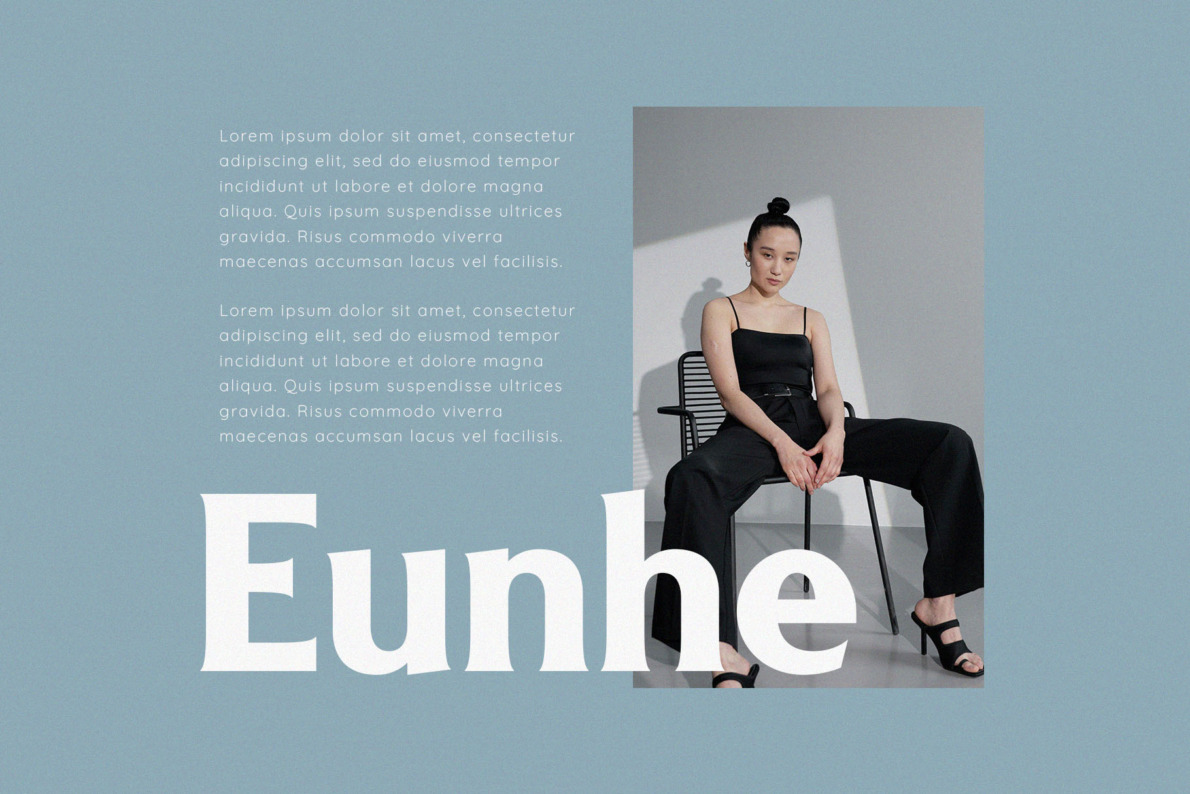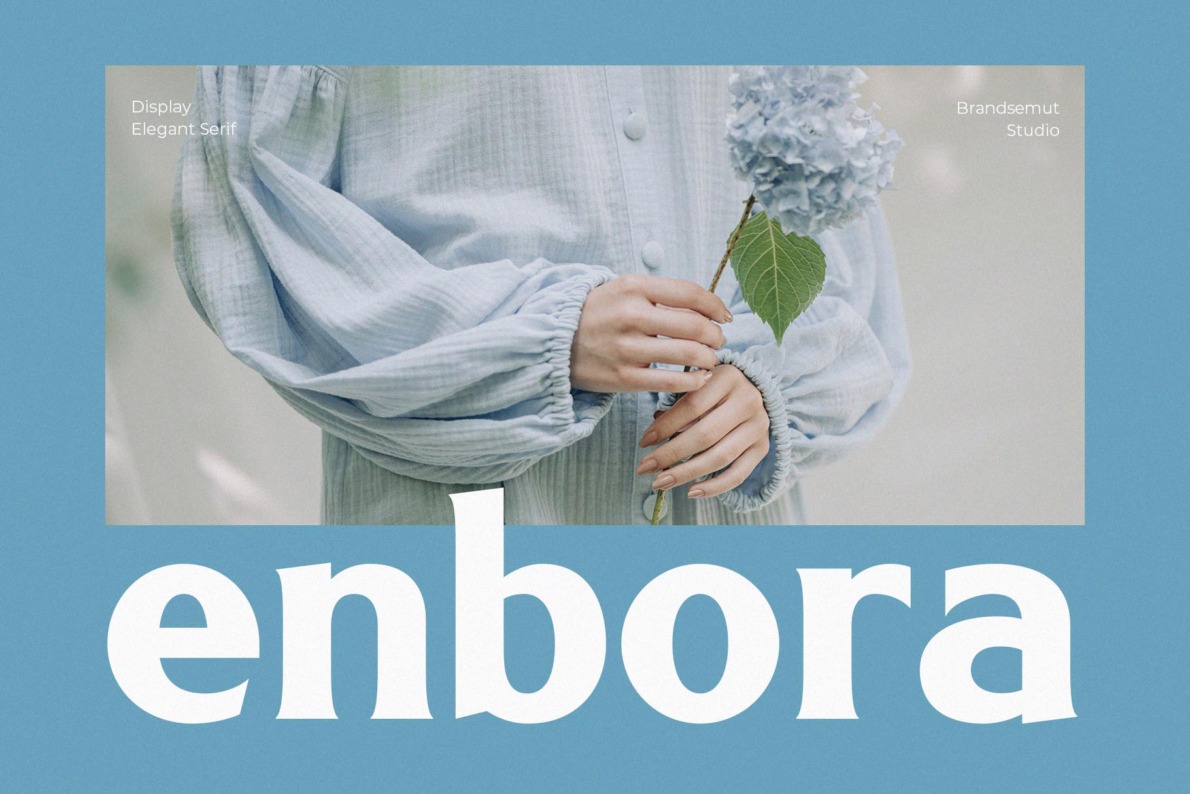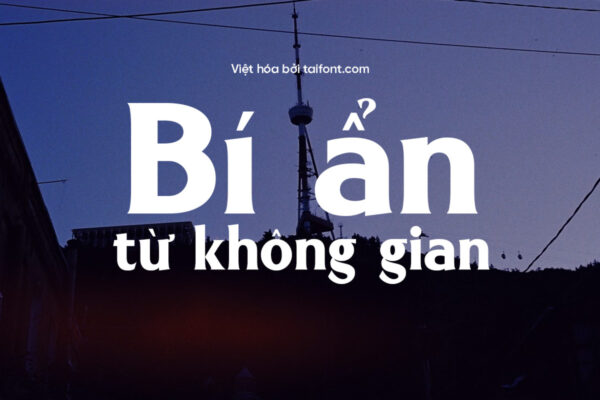
Giới thiệu về Font TF Enbora Việt hóa
TF Enbora Việt hóa là một font chữ có chân (serif) nổi bật với thiết kế nét đậm, to lớn nhưng vẫn giữ được sự tinh tế và thanh thoát. Font này mang đến vẻ đẹp cổ điển kết hợp với sự hiện đại, toát lên phong thái uy nghi, sang trọng và đầy ấn tượng, lý tưởng để tạo điểm nhấn mạnh mẽ và thu hút mọi ánh nhìn.
Với đặc điểm là kích thước lớn, độ dày ấn tượng và tính thẩm mỹ cao, Enbora là lựa chọn lý tưởng cho các thiết kế muốn truyền tải sự mạnh mẽ, uy tín và đẳng cấp:
- Thiết kế tiêu đề trình chiếu: Hoàn hảo cho các slide mở đầu, tiêu đề phần, hoặc các slide chứa thông điệp quan trọng trong các bài thuyết trình. Font này giúp bài thuyết trình của bạn trở nên chuyên nghiệp, hiện đại và thu hút sự chú ý của người nghe nhờ khả năng hiển thị rõ ràng và ấn tượng trên màn hình lớn.
- Thiết kế poster: Lý tưởng để tạo các tiêu đề chính, slogan, hoặc thông điệp quảng cáo trên poster cho phim ảnh, sự kiện, chương trình âm nhạc, hoặc các sản phẩm muốn gây ấn tượng mạnh mẽ. Nét đậm và rõ ràng của font giúp thông điệp của bạn nổi bật, dễ đọc và truyền tải một cách hiệu quả ngay từ cái nhìn đầu tiên.
- In ấn: Đảm bảo khả năng đọc tốt ngay cả ở kích thước lớn, và tạo hiệu ứng thị giác mạnh mẽ khi in trên các chất liệu khác nhau như giấy, vải, hay biển hiệu. Font này sẽ làm cho các ấn phẩm in ấn như brochure, catalogue, hay danh thiếp trở nên chuyên nghiệp và sang trọng hơn.
Với TF Enbora Việt hóa, bạn có thể dễ dàng thổi hồn mạnh mẽ, năng lượng và sự độc đáo vào các thiết kế, tạo ra những sản phẩm không chỉ đẹp mắt mà còn cực kỳ ấn tượng và có khả năng thu hút sự chú ý tối đa.
Font Việt hóa TF Enbora